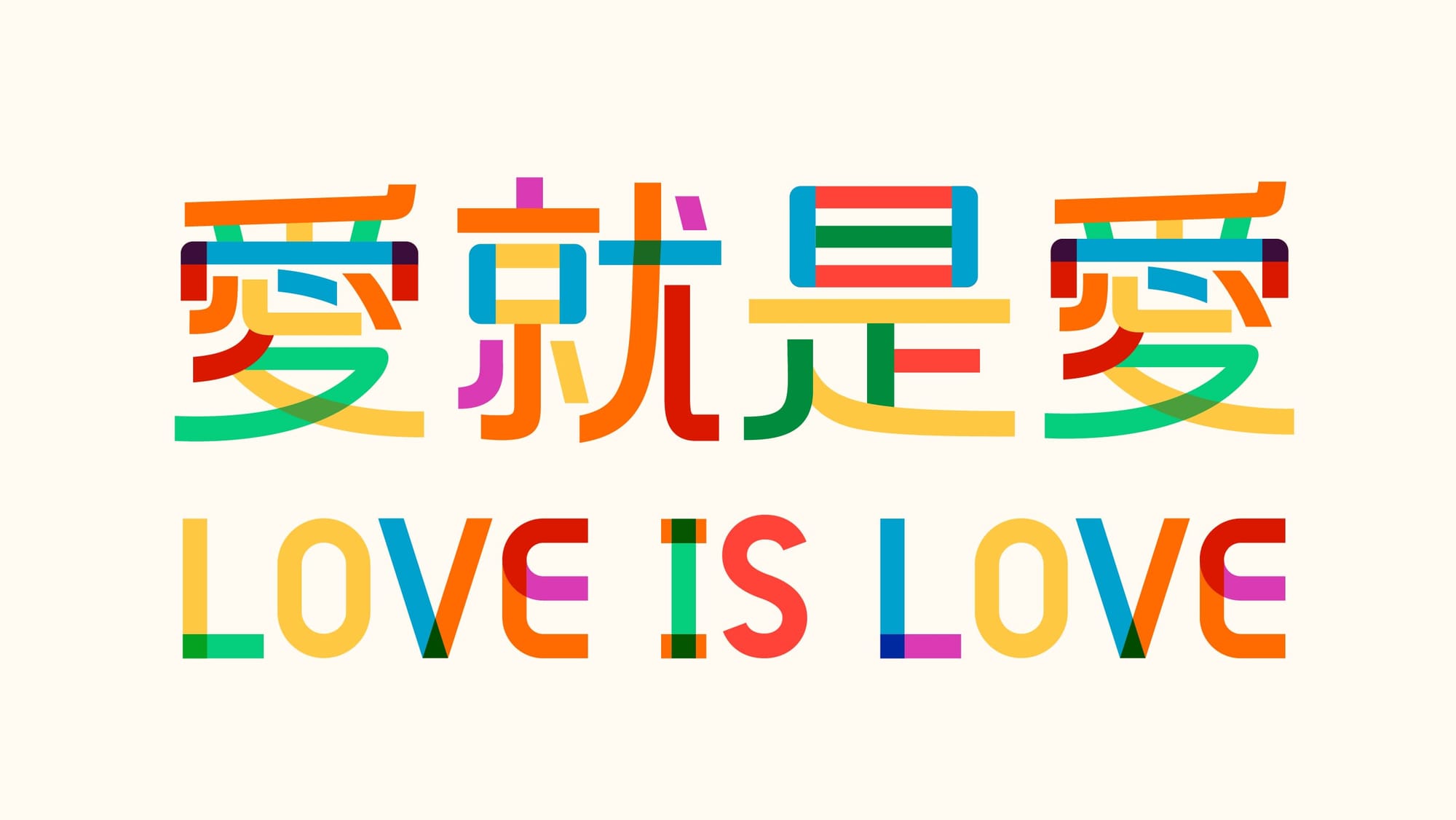
像彩虹般的字型:Color Font
開始前先來介紹 Gilbert 這款字體,它是一款自帶多種色彩的字型,用戶輸入後即會顯示繽紛的色彩,無須而外在修改。
該字體是具有象徵意義,是為了紀念 LGBTQ+ 彩虹旗的創作者 Gilbert Baker 對於社群貢獻而生,其中「色彩」是不可或缺的顏色,傳遞驕傲、多元和包容的精神。
電腦會選土豆,字體也能是彩色
其實彩色字型並不罕見,你我常用的 emoji 就是最佳實踐之一,讓我們來看看如何做到的吧!
第一步:標準化
要讓大家能正確的看到五顏六色的字體,就需要由具有一致且大部分人認同的標準與規範。
通常這幾些事會由行業內的領頭公司、組織進行,這次參戰的分別有:Microsoft、Apple、Adobe、Google,以及 Mozilla。
前面幾間相信大家都耳熟能詳,最後一間也是對網際網路有著重要影響的元老級組織,其前身為網景公司。
簡單直接:SBIX 、CBDT/CBLC
要彩色物件?沒問題,用最簡單粗暴的方法,直接塞入一張點陣圖片。Apple的SBIX (Standard Bitmap Graphics)與 Google 的 CBDT/CBLC(Color Bitmap Data / Color Bitmap Location)之方法就是如此。
看名稱就知道,是直接將一張點陣圖放入編碼中。這種做法可以讓物件保有真實世界的質感,但也因為是點陣圖,因此放大存在失真的可能(會有鋸齒邊),且因為是圖片,加總起來檔案容量也不小。
進階:OpenType-SVG
聰明的你一定知道,如果點陣圖會失真,那就放向量圖啊!Adobe 與 Mozilla 也是這麼想的,他們希望在字形中鑲嵌 SVG 格式的圖檔。這讓彩色字型可以無限放大,但是無法單獨改顏色,如果想要製作出非裔、華裔...等,膚色較多元的同個表情符號,就需要一個一個單獨建立,且以 Chromium 為核心的瀏覽器都不支援,會直接顯示黑色。
以 Adobe EmojiOne 為例,同樣的「比讚」符號,有六種膚色,就需要單獨繪製 6 張 SVG 圖檔,並一一嵌入。
更上一層樓: COLR/CPAL
計算機領域中,哪能缺少我們 M大 – Microsoft。他們提出的方案一樣是向量圖形,但是同個圖形中,拆分多個圖層,並記錄圖層、色彩等資訊。
同樣以「比讚」符號為例,如果用 COLR/CPAL 技術,只需要繪製 3 個字符框,透過改變不同圖層顏色,即可做到多種顏色效果。
普羅麥克斯: COLR/CPAL V1
在此之後 Microsoft 又與 Google(對,他又來了)提出擴充,允許加入更多屬性,例如:Alpha 值,也就是允許透明度與漸層,甚至是混合模式。為 Color Font 帶來更多可能性。
2024 年在微軟更新了新版 Segoe UI Emoji 就是使用 COLR/CPAL V1 完成,在 Windows 11 中就是使用該字型,預設會出現 3D版本,如果軟體不支援,則會跳回2D版本。
隨堂測驗:
請問根據以下圖片 Gilbert Color 最有可能是使用何種技術呢?提示:該字體為向量外框